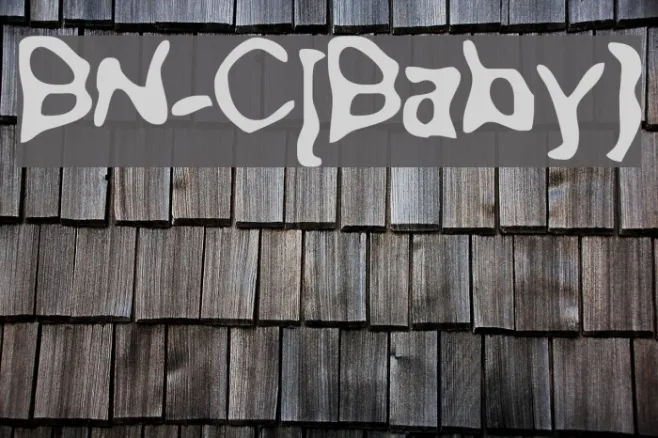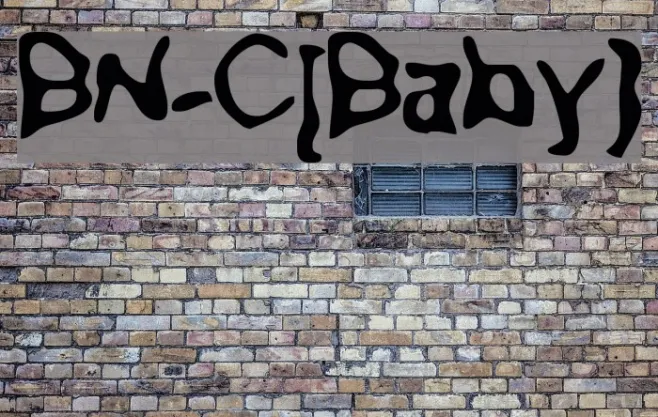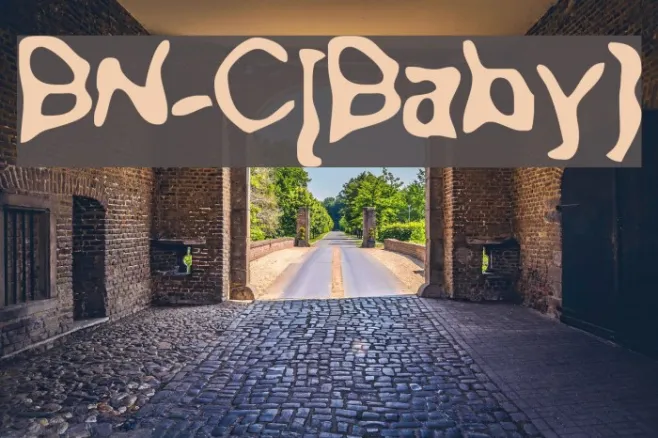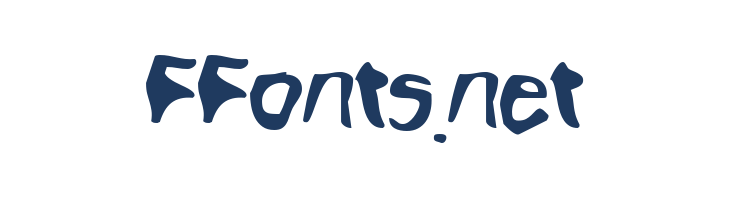
BN-C[Baby] Font
Fonts by Ben Nathan
| Stile generale | Playful, Whimsical |
| Caso d'uso | Headlines, Posters, Creative Projects |
| Progetti proposti | Ideal for children's books, playful branding, posters, and creative projects that require a fun and energetic typeface. |